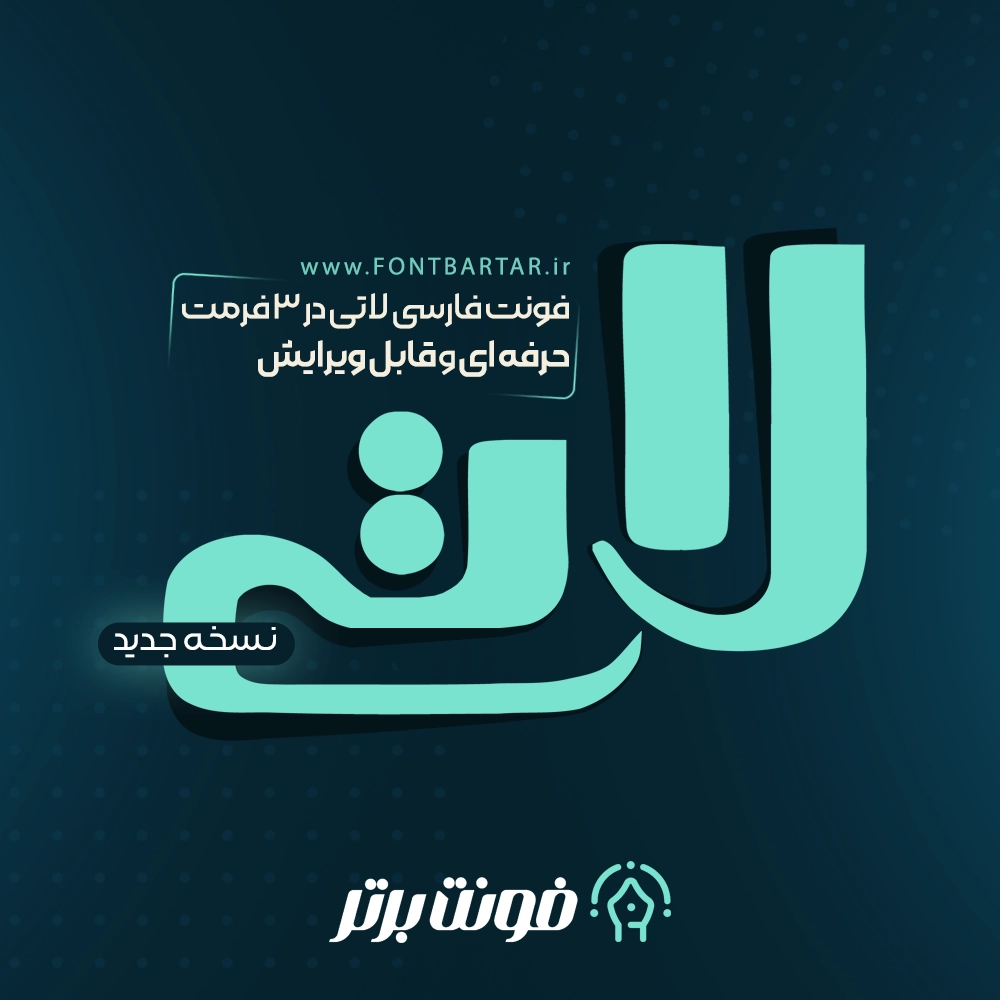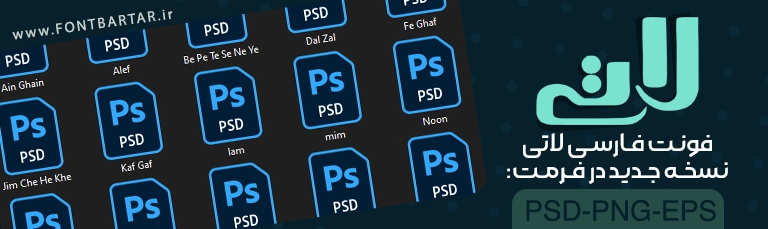
دانلود فونت لاتی – فونت فارسی حرفهای برای طراحی لوگو و تایپوگرافی
فونت فارسی لاتی اگر به دنبال یک فونت فارسی حرفهای هستید که بتوانید با آن لوگوهای خاص، پوسترهای تبلیغاتی و طراحیهای تایپوگرافی جذاب خلق کنید، فونت لاتی انتخابی فوقالعاده است. این فونت با ساختاری مدرن و ترکیبی از خطوط نرم و قدرتمند، مناسب برای استفاده در طراحی لوگو، کاور موزیک، پوسترهای سینمایی، بنر تبلیغاتی و محتوای شبکههای اجتماعی است.
فونت لاتی بر خلاف سایر فونت ها به صورت لایه باز بوده (psd) و امکان تایپ مستقیم در نرم افزار ها را ندارد همچنین شامل تمامی حروف از الف تا ی می شود این فونت به چینش های مختلف می تواند در کمترین زمان این امکان را به طراح بدهد که یک لوگو تایپ حرفه ای برای کسب و کار های مختلف طراحی کند ویژگی های این فونت حرفه ای را باهم مرور کنیم.
ویژگیهای فونت لاتی
- مناسب برای طراحی لوگوهای مدرن و حرفهای
- قابل استفاده در تایپوگرافی و طراحی پوستر
فونت فارسی لاتی دارای حروف های متفاوت:
چرا فونت لاتی انتخابی عالی برای شماست؟